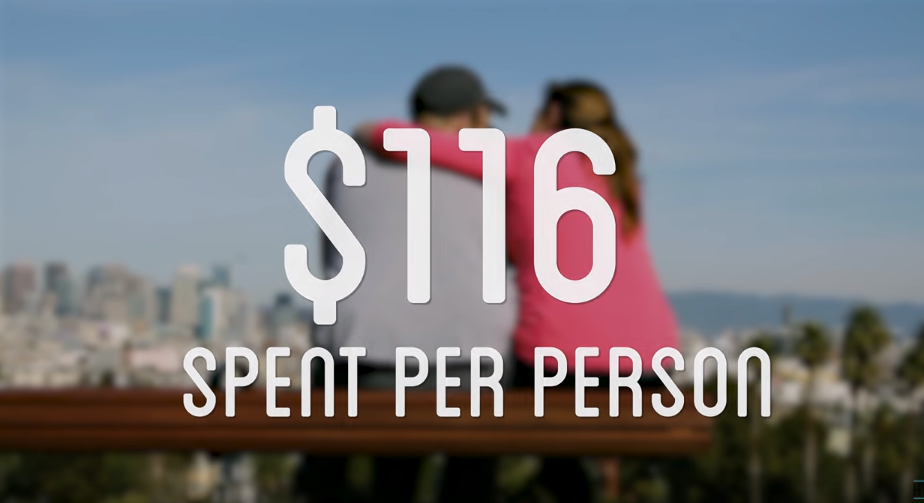
Suche Name dieser Sans rounded, ähnlich wie ‹Spoon›.
Hallo. Ich habe schon ein wenig gesucht, kann aber den Namen dieser Schriftart nicht herausfinden. Die Schriftart ‹Spoon› sieht zwar sehr ähnlich aus, ist es aber leider nicht. Kann jemand die Schrift identifizieren? Dieser Screenshot ist von einem YT-Video und in dessen Beschreibung wie auch den Kommentaren steht leider nichts davon.
ingo_k Danke das ist es! Sie hat gleich mein Auge umschmeichelt, leider nur als Versalien, trotzdem schön.